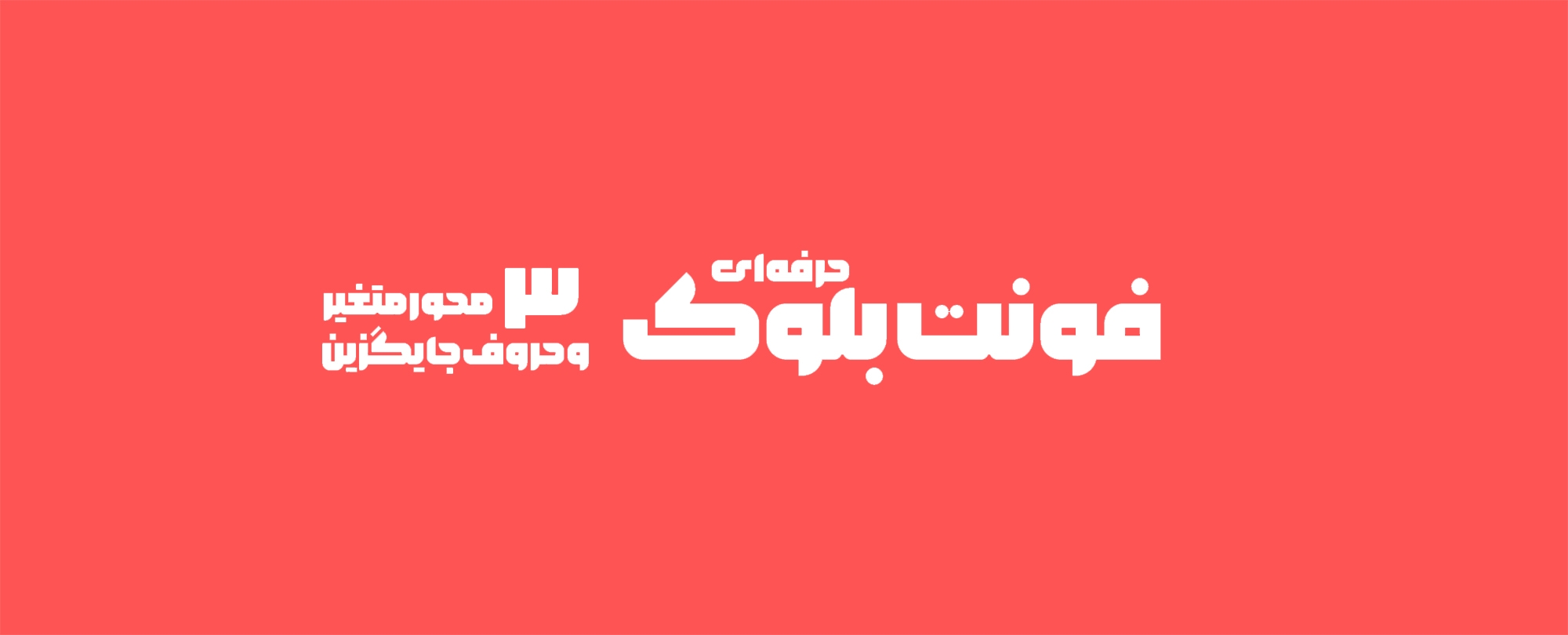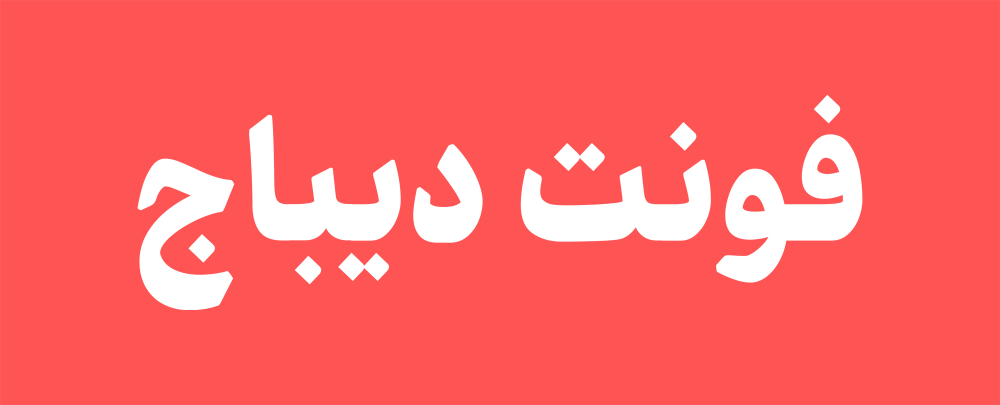
فونت بلوک با کنار هم گذاشتن بلوکهای مربع و مستطیل ساخته شده است.
بلوک فونتی ساده، هندسی و منظم است، و به دلیل وزن سنگین بیشتر برای استفاده در عناوین کوتاه مناسب است.
در دیزاین حروف بلوک از خط کوفی بنایی یا معقلی الهام گرفته شده ، خط بنایی یا معقلی به دلیل ارتباط عمیقش با آجر و ساختمان ساختار مبتنی بر مربع و مستطیل داشته است.
تایپفیس بلوک دارای دو استایل نرم و سخت یا Round و Sharp است که هرکدام از آنها شخصیت متفاوت و مجزایی دارند و بهتر است متناسب با موضوع و محتوا از آنها استفاده نمایید.
فونتی مناسب تایپوگرافی و استفاده در طراحی پوستر و کاورهای خلاقانه.
فونت دیباج روایتگر است. روایتگر داستان ها، اتفاقات و رویدادهای زندگی با لحنی صمیمی. این تایپفیس از ابتدا برای کاربرد در متن های بلند داستانی، طراحی شد. بنابراین خوانا بودن در کنار داشتن لحن صمیمی و روایتگر اهمیت فراوانی داشت.
از جمله عواملی که برای حفظ خوانایی در اندازه متن (pt12~7) مورد توجه قرار گرفتند، حلقه های نسبتا بزرگ، خطوط کرسی منظم و محدود، رعایت اصول فاصله گذاری درستِ متناسب با ریتم و فرم حروف برای ایجاد خاکستری متن سالم و اغراق در محور عمودی حروف بوده است.
متناسب با این اهداف برای طراحی فونت دیباج از خط محقق الهام گرفته شد. و تلاش بر این بود تا دیباج علاوه بر پایبندی به ریشه خود، مدرن و امروزی باشد.
فرم منحنی حروف ( نسبتِ دور بیشتر) باعث حرکت راحت تر چشم بر روی سطرها شده و و آن را تبدیل به فونتی روان و سیال کرده است.
فونت دیباج دارای 9 وزن است که وزن های پایه آن برای استفاده در نوشتههای بلند در کتاب و مجلات و… مناسب هستند و وزن های ضخیم آن برای آثار گرافیکی و تبلیغات. در وزن های ضخیم تر این قلم از دور حروف کاسته شده و فراز و فرودها کوتاه تر شده اند تا انسجام بیشتری برای نوشتن عنوان نوشتار داشته باشند و نگاه مخاطب را جذب کنند. دیباج یک قلم کامل برای پاسخ به تمام نیازهای نوشتاری دریک پروژه ست.
وزن های light و Ultra-Light آن، به دلیل دور متعادل، کنتراست ضخامت کنترل شده ، فضای منفی مناسب در حلقه ها و کاسه ها و نیز کرنینگ و ترکینگ درست و سالمش، گزینه خوبی برای استفاده در طراحی اپلیکیشن ها است.
فونت پیکان به وضوح متاثر از خط نسخ و فونتی جسور و جدی است. تغییر جهت ناگهانی حرکتها و کنتراست ضخامت بسیار افراطی از ویژگیهایی است که فونت پیکان را بسیار خاص و متفاوت کرده است. اسکلتی پر از خطهای صاف دارد و تنهاش پر از فرمهای تیز و بُرنده است و به هرجا بخورد آسیب جدی وارد میکند! «هنگام استفاده احتیاط کنید و فونت پیکان را از دسترس کودکان دور نگه دارید».
پیکان به معنی تیز، نیزه، فلش و نام یکی از خودروهای سواری پراستفاده در دهههای ۶۰ و ۷۰ شمسی در ایران است.
فونت پیکان مناسب استفاده در نوشتههای کوتاه و تیترهایی است که باید در یک لحظه جلب توجه کند. از این فونت میتوانید در دیزاینهای مرتبط با فشن و برای برندهای لوکس استفاده کنید. همچنین بهخاطر لهجهاش برای محصولات وارداتی هم مناسب است.
الگوی اصلی رضا بختیاری فرد برای طراحی پیکان، فونت شفیق بوده است. جسارت و لهجهی دوستداشتنی شفیق، طراح فونت پیکان را مشتاق کرده تا فونتی با این اتمسفر اما با اغراقهایی بسیار بیشتر طراحی کند.
برای زبان لاتین از فونت اوپنسورس Newsreader استفاده شده است؛ با اعمال تغییراتی در تناسبات و ضخامتها.
ونت صنعت یک فونت سنگین وزن هندسی است که تداعی کننده طراحی حروف ایرانی در دهه ۵۰ است. حروفی سنگینی که بیشتر در ساخت تابلو سردرها و لوگوتایپهای صنعتی مرسوم بود. به همین دلیل فونت صنعت با وجود مدرن بودن دارای حس و حال نوستالژی است.
طراح این تایپفیس (مجید شعرای نجاتی) میگوید: ایده اولیه این فونت از طراحی چندین لوگوی صنعتی شکل گرفت . نیاز به فونتی با وزن سنگین و ضخامت زیاد برای ایجاد کلماتی مناسب با فضای صنعتی از اولین گام های شکل گیری این پروژه بود.
این فونت فقط یک وزن دارد اما دارای تعدادی حروف جایگزین است که میتوانید به دلخواه آن را تغییر دهید.
فونت همراه برداشتی ساده از خط بنایی است، استخوان بندی محکم و استوار دارد و هندسه آن متشکل از خطوط مستقیم است.
کلیت فونت همراه از یک گرید پیروی میکند و حروف شخصیت جدی در عین حال صمیمی دارد
چشم ها کوچک طراحی شده و فضای منفی داخل حروف و همچنین محیط کلی حروف بسیار کم است و حروف به خط کرسی نزدیک هستند که این باعث تاثیر گذاری و هماهنگی بیشتر شده است.
نقاط ضعف و قوت در فونت همراه بسیار نزدیک هم هستند.
تمام حروف به ساده ترین شکل طراحی شده اند اما هرکدام شخصیت نو و جدیدی دارند.
فونت همراه یک وزن دارد و مناسب استفاده در نوشتههای کوتاه است.